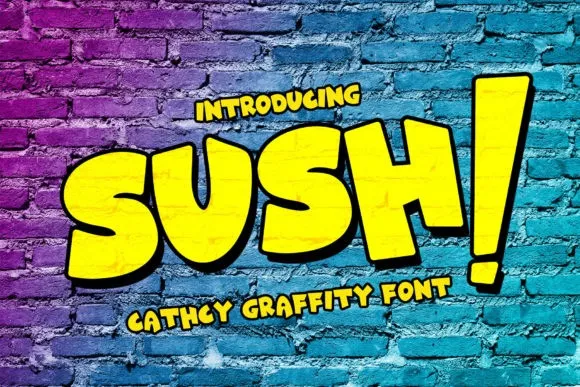
SUSH! Font – Fonte Grátis
SUSH! Font
Esta é uma fonte de exibição bold e estilizada criada para destacar seus projetos visuais. Desenvolvida pelo designer font tinyhandletter, ela é perfeita para designs artísticos como marcas, logomarcas, entradas de blog, arte personalizada, frases inspiradoras e muito mais! Além disso, a Sush! é PUA (Private Use Area) encoded, o que significa que você pode acessar todas as gílias e curvas alternativas facilmente. Engane-se se pensar que essa fonte está apenas para quem quer destacar sua identidade visual; ela é uma ferramenta versátil para qualquer tipo de projeto visual criativo. Experimente a Sush! em seus próximos projetos, e veja como pode mudar o aspecto de seu design.